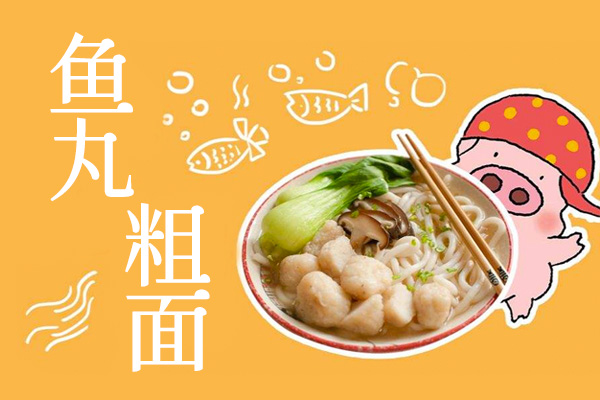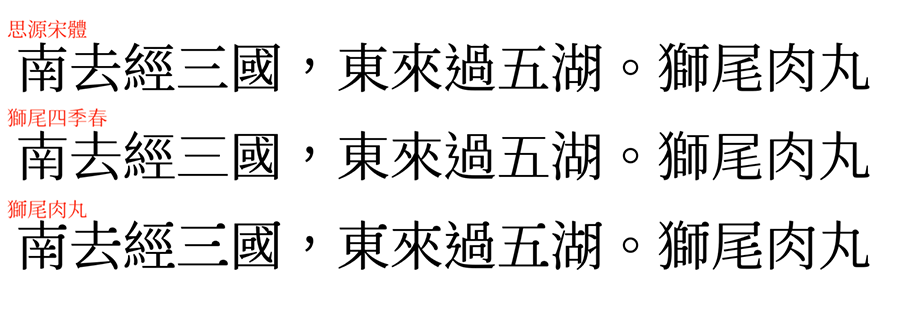
狮尾肉丸体
狮尾肉丸体(Swei Meatball CJK TC)是台湾设计师MAX基于思源宋体改造的全新字体。他们将思源宋体的三角形替换为半圆形,使其更现代化。此字体支持简、繁体中文,韩文和日文,且拥有7个字重,满足各种设计需求。
此款字体与电脑书法字体的不同之处在于,它将三角形替换为圆形,类似于日本的可爱字体。尽管日本字体有许多细致之处,但其汉字数量远少于中文字,更容易出现缺字现象,且日文汉字的笔顺与中文不同。
与思源宋体相比,狮尾肉丸体的设计更现代、清新。它基于思源系列字体,通过人工智能程序进行批量处理,因此拥有超大的字符集,简、繁体基本无缺字。
狮尾肉丸体效果预览